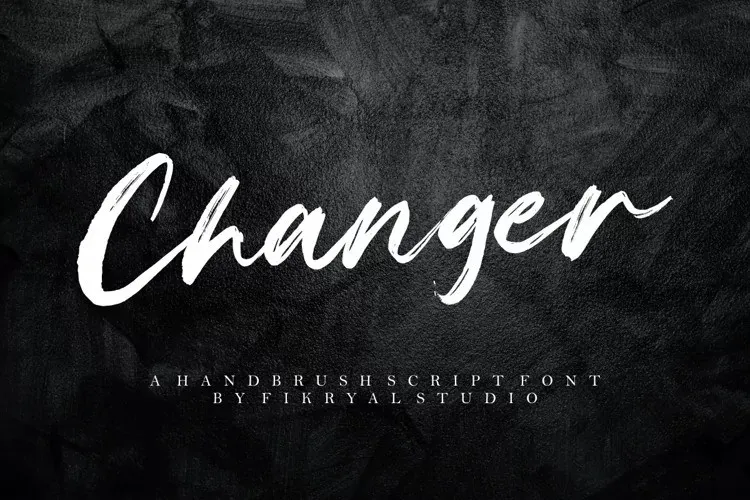
Changer Font – Download Grátis
A fonte “Changer Font” é uma elegante tipografia script brush criada pelo designer fikryal. Ela carrega um ar casual mas também exibe sutilezas que a tornam perfeitamente adequada para diversos tipos de projetos. Suas linhas delicadas e seus traços leves fazem dela uma escolha ideal para criações como logotipos, rótulos, embalagens de produtos, designs web, revistas e posts no Instagram. Seu estilo moderno e elegante a tornam adequada não apenas para projetos comerciais, mas também para publicações pessoais ou eventos especiais. A Changer Font é uma fonte ideal para designers que buscam um equilíbrio entre elegância e simplicidade em suas criações digitais.